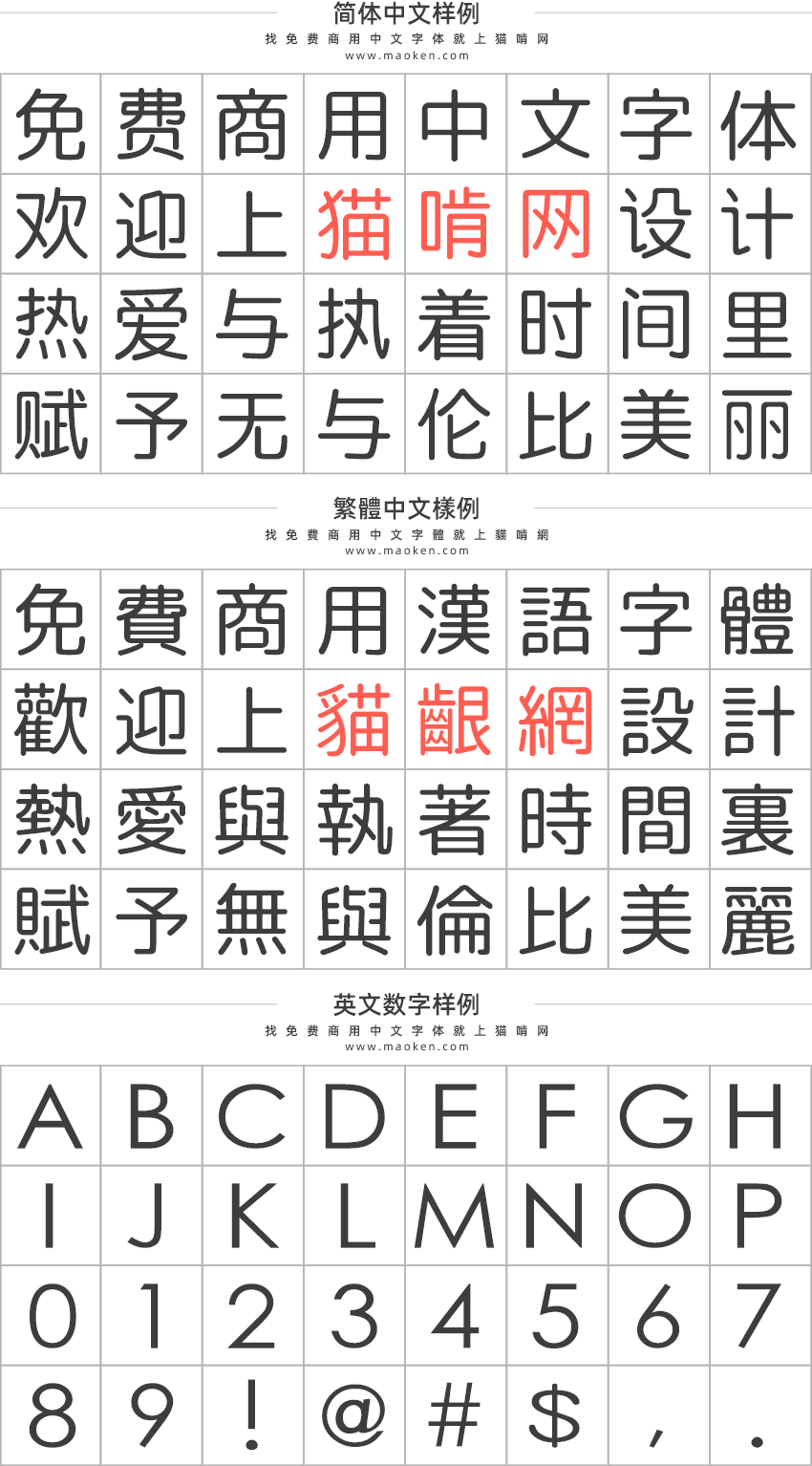
源柔黑体是日本设计师基于日本版思源黑体改造而成的字体,支持的简体字符比较少。而源柔黑体凤殿强化版是国内的设计师凤殿基于日本的源柔黑体改造的字体,添加了简体部分的汉字,所以这款字体无论是简体还是繁体都基本上不缺字。不过可惜的是这款字体只有一个字重。如果想要多个字重简体又不缺字的字体,推荐使用台湾设计师改造的源泉圆体。
此款的补字部分字体,经猫啃网友@Restart对比,疑似使用了非免费商用的华康圆体。所以这款字体猫啃网不建议用作商业用途。
非常不建议各位用这款字体,字体的细节完全经不起考察和推敲,像是随便拿铅笔工具画了一下,图里的是非常明显的几处。此外,不同汉字去对比的话,也会发现圆角的大小等地方都没有进行统一,很乱。https://s21.ax1x.com/2024/06/25/pksDUZd.png
非常不建议各位用这款字体https://s21.ax1x.com/2024/06/25/pksDUZd.png
这个字体可能也属于用版权字体补全的字体,简体部分(尤其是「设计时间伦丽」这六个字)可能采用的是华康黑体 W5。 https://s3.ax1x.com/2020/12/21/r0IkGT.png